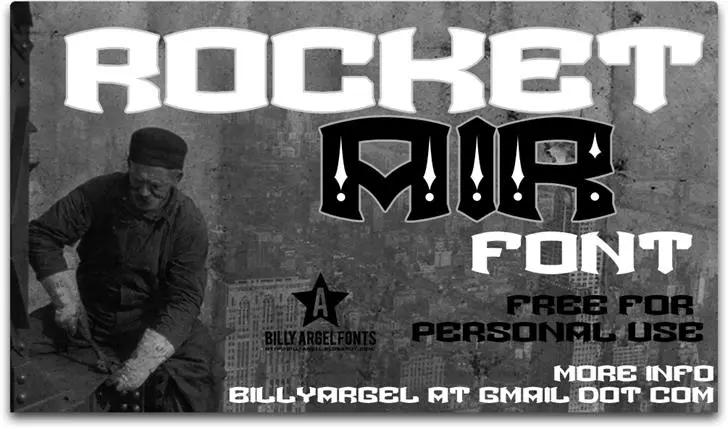
A ROCKETAIR Font é uma elegante e poderosa fonte símbolo criada por Billy Argel, disponível na categoria de fonts simbólicas. Este design destaca-se pelo seu formato curvilíneo, que incorpora elementos aerodinâmicos e futuristas. Seu estilo atemporal combina um leve arquitectónico com uma sensação tecnológica, o que a torna perfeita para aplicar em designs de marca ou símbolos de produtos inovadores. O designer Hamilton criou esta fonte sob medida para estilos gráficos modernos e futuristas. Suas linhas fortes e curvas arredondadas dão um toque dinâmico, combinando bem com qualquer tipo de arte digital ou design gráfico que exija personalidade. A ROCKETAIR é ideal tanto para uso em logotipos quanto em materiais publicitários, oferecendo uma combinação única e inovadora que destaca sua marca. Para mais informações sobre a fonte, você pode entrar em contato diretamente com Billy Argel através do  ou visitar seu site, o billyargel.com. Além disso, Hamilton também disponibiliza recursos adicionais para quem deseja explorar ainda mais as possibilidades da ROCKETAIR Font.